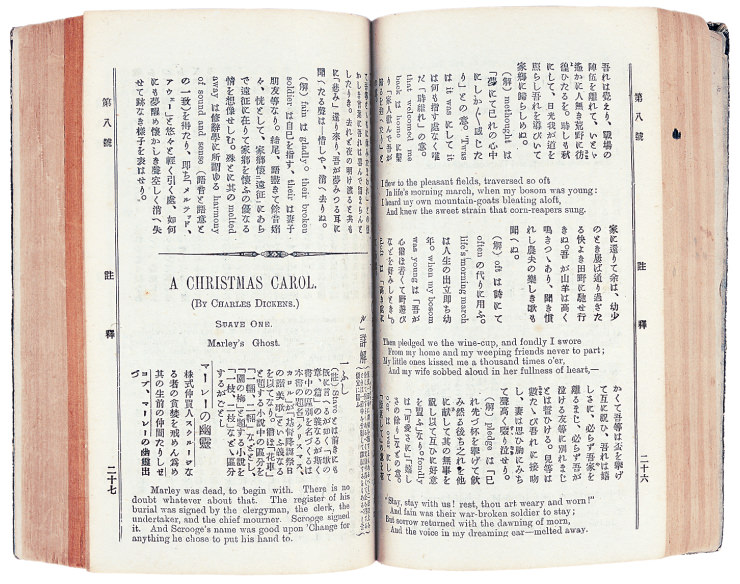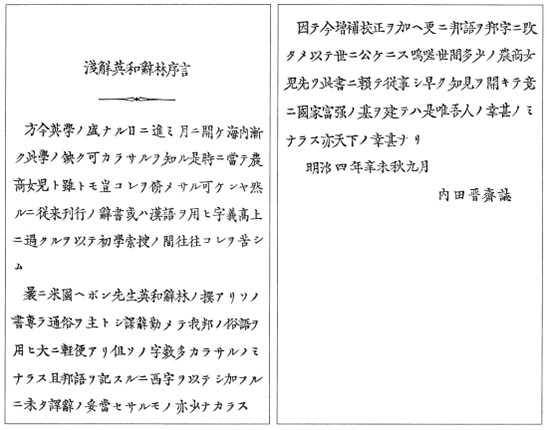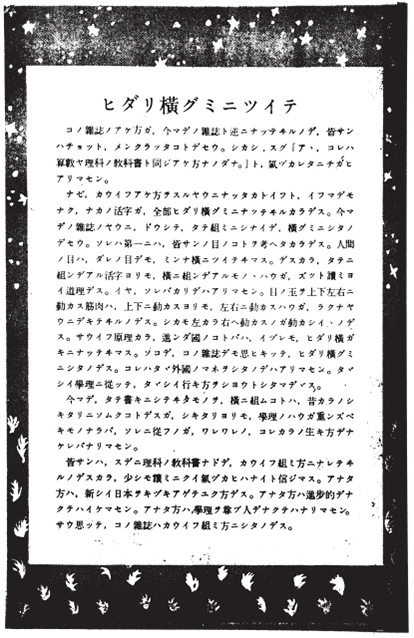
第三回 日 本 語 の 組 み 方 2 欧 文 組 み
よくいわれるように、日本人は外来文化を咀嚼して自らのものとすることに長けています。古代は中国や朝鮮半島から、近代はヨーロッパから、また第二次大戦後はアメリカから、それぞれ多大な影響を受けてきました。
日本には、「日本文化」という独自の文化があると考えられています。しかしそれは、外来文化に対する対抗文化のような性質を持っており、つねに主体は外にあるようにも見受けられます。ですから、“影響”とはまた違って、外来文化は、自国の文化をかたちづくる原動力であったのかもしれません。
いずれにせよ、日本という国が、一国だけで成立するはずもなく、古代から近世にかけては東アジア文化圏に、現代では地勢的な枠組みを超えた高度資本主義文化圏に属していることは間違いありません。
中国主導の東アジア文化が日本語の「漢文組み(均等字送りを基本とした文字組み)」を作ったように、西洋の文化も日本語組版に何らかの影響をもたらしたのでしょうか。
和欧
混植
外来語をカタカナで表記するようになったのはいつごろのことでしょう?はっきりと調べたことはありませんが、たぶん江戸後期にはすでに行なわれていたものと思います。
カタカナは、漢字の偏や旁の一部だけを採ったもので、漢文の横に読みを書き添えたりするときに使われていましたから、外来語をカタカナで書くことは、自然に受け入れられることだったのでしょう。もともと漢字を倭語にあてて読んだ万葉仮名も日本語に漢字を振ったものとも言えますから、音にしたがって文字を振るのはお手のものだったに違いありません。
かつて、洋画は日本語題で(翻訳して、または、まったく違う題名をつけて)公開していました。たとえば、ヒッチコックの「鳥」の原題は「The Birds」で直訳ですが、ニューシネマの名作「明日に向かって撃て」は「Butch Cassidy and the Sundance Kid」で、まったく違うタイトルになっています。
こういういわゆる“邦題”には味のある忘れがたいものも多いのですが、ここ10年ぐらいは直接カタカナ書きする題名が多くなっています。しかも「パイレーツ・オブ・カリビアン~ワールド・エンド」(原題は「Pirates of the Caribbian: at World’s end」)のように、適当にカタカナ英語にされているものもあって、子供も観る映画なのにこれでいいのかと心配になります。また、最近は「Into the Wild」のようにそのままアルファベットで表記するものも出てきています(ちなみに「Into the Wild」の原作は、『荒野へ』という翻訳題で日本でも出版されています)。
長々と何を書いているかというと、日本語の中に、本格的にアルファベットが混ざりつつあるということを言いたいのです。映画のタイトルも日本語題から外国語のカタカナ表記、そして原文表記へと変わってきました。
日本語は仮名漢字混じり文であることは言うまでもないのですが、そこにラテンアルファベットも混ざるようになってきたのです。
日本語は、構文が正しく、助詞や助動詞が日本語でありさえすれば、日本語として認知できます。たとえば《Theater で「Into the Wild」を enjoy した》でも、日本語として通じるということです。また、NASAやHTMLなど、アルファベットでしか表記できないことばも増えて、ますます和欧混植率が高まっています。このことは、昨今の欧文タイポグラフィへの興味とも無関係ではないでしょう。
「日本英學業新誌」
明治25年(1892)創刊
英文は横組み邦訳は縦組みで記載されている
横転横書きの例(明治34年)
左横書き
もう一つの重要な西洋文化からの影響に「左横書き」があります。左から右へ横に文字を並べて書くのはいつごろからはじまったのでしょう?屋名池誠氏による、詳細な研究、『横書き登場 ─日本語表記の近代─』(岩波新書)を見ながら、話しを進めたいと思います。
同書に、公刊物での左横書きの最初の例として、明治4年(1871)に刊行された『浅解英和辞林』が挙げられています。想像に違わず辞書がはじまりなのですが、どうもそれは、大型の本格辞書ではなく、簡便な小型本で、その外見どおりに中身も怪しげなものだったということです(当時、書物の格式はそのサイズによってあらわされていました)。なにやら、版権侵害で訴えられていたような、あやしげな本ということですが、左横書き、洋式(グーテンベルグ式)活版印刷という新機軸を打ち出しており、ある意味、意欲的な出版物だったようです。その後、左横書きされる語学書が立て続けに出たことをみても、追従されるほど影響力があったことがわかります。それまで辞書は、「縦書き右方向行移り(左から右へ行を進める)」「横転縦書き(縦書きを90度回転させる)」などの工夫でしのいでいたのですが、ついに、真打ちの「左横書き」が登場したのです。しかし…と、同書は進みます。
しかし、世界的に見れば、縦書きから横書きへの移行は横転横書きが普通なのに、なぜ日本語が左横組みへと展開したのか。同書はそれを、横書きに不利にならない枡目組版だったためと解いています。前回でお話しした「漢文組み」つまり、漢文のように組むために連綿のひらがなをひと文字ずつに分断し、正方形の枡目に埋め込んだことが、日本語の左横組みを可能にしたというのです。
縦書き枡目組版信奉者ほど横組みを嫌うことを思い起こせば、不思議なことですが、“ふるまい”が先にあって技術を作るのではなく、技術から“ふるまい”が生まれる例はどこにでも見ることができます。これもそのひとつなのでしょう。
外国の書字方向に影響を受けて、自国のことばをまねて書いてみることは、よくあることです。20世紀初頭の日本文化の影響を受けたヨーロッパでは、縦書き(横転縦書き)にした添え書きがたくさんありますし、日本でも、江戸時代後期の錦絵に、横転横書きを見ることができます。しかし、そういった新しい書字方向が定着することはきわめて稀です。なぜ日本に左横組みが広まっていったのか、それについて『横書き登場』はこう述べています。
──日本語に新しい書字方向が生じたのは、当時の日本社会にそれを受け入れる社会的条件がたまたま備わっていたからだ。そういう意味で、日本語における横書きの成立は、時間と空間の条件に制約された一回性の歴史的な事件だったのである。──
その「社会的条件」とは、明治の西欧文化への傾倒とあこがれにほかなりません。昭和戦後すぐに創刊された児童雑誌に掲載された左横組みへの(今読めば噴飯ものの)啓蒙も、敗戦国日本が欧米に追いつきたいという気持ちがエンジンになっていたのでしょう。文中にある《進ンダ國ノコトバハ,イヅレモ,ヒダリ横ガキニナッテヰマス》という一文がそれをあらわしています。左横書きが一般に定着するのは、1960年以降のことです。
では、書字方向の変化が日本語タイポグラフィにもたらしたものはなんだったのでしょうか。
最初の左横書きの刊行物
『浅解英和辞林』(明治4年)
左横組みに縦組みのふりがな(昭和35年)
1960年代に入ってもまだ安定していなかったことが伺える
「ヒダリ横グミニツイテ」(昭和21年)
児童雑誌『銀河』(新潮社)に掲載された解説
プロポー
ショナル
組み
組版は、字間、行間、段間など、スペースを決めていく作業であることは、第1回で述べました。スペースはドーナツの穴と同じでドーナツ本体がそれを決定します。つまり、どこからどこまでを文字と見なすかがスペースを決める重要な要素になります。 たとえば、ボディ(仮想ボディ)全体を文字と見なすとします。そうすると、前回紹介した漢文組み、つまり枡目組版は、均等字送りで、かつ字間も均等にあいていることになります。しかし、文字のかたちそのものを基準にすると、枡目組版の字間は不均等ということになり、文字ごとのプロポーションに添った字送りの方がアキが等しくなります(第1回図版参照)。この文字のかたちを基準に字間を決めていく組み方を「プロポーショナル」と呼んでいます。 ラテンアルファベットは、i, a, m など文字の幅に差がありますから、活字時代から文字の幅にしたがってボディの幅も変えて、プロポーショナル組みを実現していました。しかし、AVなど文字を食い込ませないと均一のアキが得られないものに関しては、やはり、ボディに添ってあいたままになっていました。和文、欧文とも、正確なプロポーショナル組みを手に入れたのは、写植以降、つまり、活字のボディから解放されてからのことなのです。 しかし、一口に字間を均等にあけるといっても、なかなか難しいものがあります。たとえば、「もじ」のように同じようなかたちの文字が並ぶ場合と、「もつ」のように左右にふくらんで空間が真ん中にできる場合では、同じだけ文字と文字の間をあけても、均等には見えません。プロポーショナル組みの場合、“目で見て”間隔を調整する必要があります。つまり、ひとによって上手、下手ができる組み方とも言えます。
欧文
組み
活字の時代から清刷りを切り貼りして詰めたり、写植では詰め情報を持っている文字盤がつくられたり、プロポーショナルに文字を組む欲求は以前からありました。しかし、和欧混植、左横組みにともなって、急速に普及してきたことも確かでしょう。
枡目に文字が整然と並ぶ縦組みとは違って、“見え”の字間を均等に調整し、全体の濃度を均質に近づけ、横のラインもすっきり整えて見せる方法は、欧文組版からの影響が色濃く見られます。左横組みでプロポーショナルな組み方は、欧米の文化とアルファベットへのあこがれが育てた日本語組版=欧文組みといってもいいでしょう。
均等字送りの縦組みが漢文に倣った「漢文組み」で、プロポーショナルの横組みが「欧文組み」であるなら、日本語独自の組み方はいったいどこにあるのでしょう。それを探すべく、次回からは、技術と組版の関係について見ていきたいと思います。